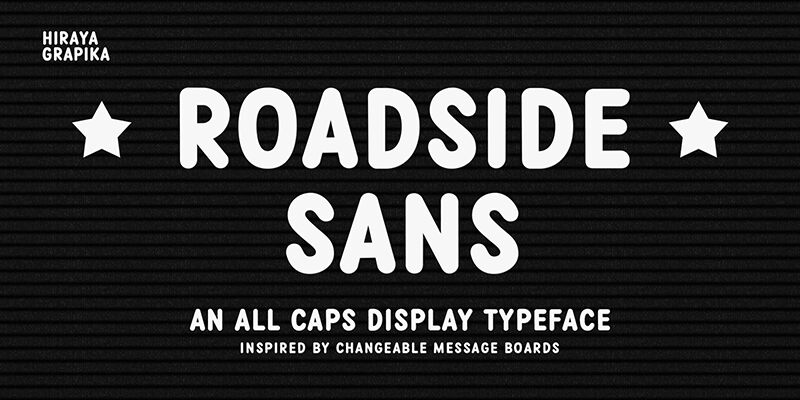
Roadside Sans, créée par Emmanuel Ludovice / Hiraya Grapika, est une police de caractères « display » gratuite au style cartoon, dotée de formes arrondies et verticales ainsi que de courbes douces et larges qui lui confèrent l'aspect d'un lettrage fait main rappelant les panneaux de bandes dessinées. Ses formes restent simples et fluides, dépourvues d'angles vifs, ce qui donne à l'ensemble un rendu convivial et robuste, sans jamais être trop complexe.
Roadside Sans est parfaite pour les titres d'affiches, les emballages pour enfants, les graphismes de jeux vidéo, les logos et les textes courts sur des produits dérivés où une police arrondie doit faire preuve d'un caractère clair et accessible. Cette police gratuite est également idéale pour les flyers d'événements et les enseignes de magasins, car sa construction simple assure un lettrage homogène et facile à intégrer dans des mises en page qui demandent une touche graphique marquée.
Roadside Sans est une police de caractères « display » arrondie, semi-condensée et uniquement en majuscules, inspirée des lettres audacieuses des panneaux d'affichage rétro à caractères interchangeables.
Roadside Sans is a rounded, semi-condensed, all-caps display typeface inspired by the bold letters of retro changeable sign boards. Rooted in the charm of mid-century roadside culture, it captures the friendly confidence of lettering that announce daily specials, welcome guests, or catch the eyes of passerby. Its clean geometry, softened edges, and subtle hand-drawn feel bring a balance of utilty and warmth, making it as approachable as it is attention-grabbing.
Designed for clarity, impact, and character, Roadside Sans shines in logos, packaging, posters, menus, and signage that call for a touch of retro authenticity. Perfect for crafting a nostalgic identity or a modern design with vintage flair.